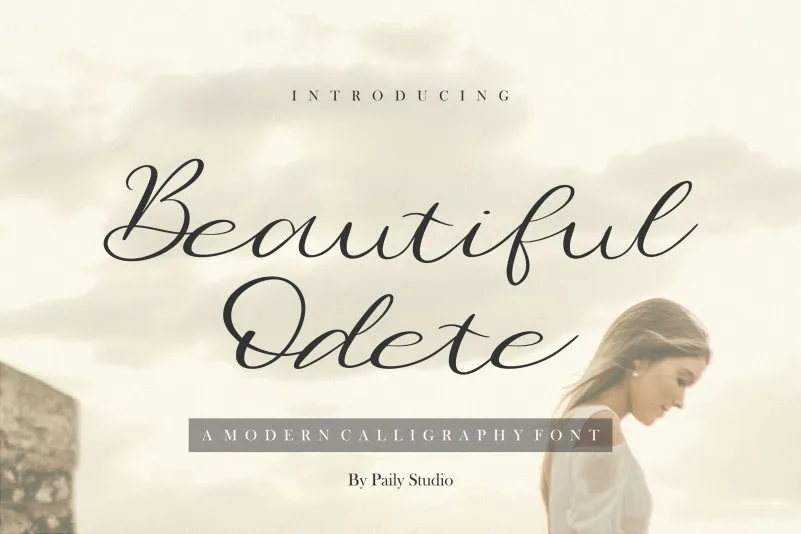
Beautiful Odete Font – Fonte Grátis
Beautiful Odete Font
A Beautiful Odete Font é uma delicada e sofisticada opção para designers que buscam adicionar um toque único a seus projetos de arte digital. Inspirada no belo estilo do caligrafia oriental, esta fonte garante uma presença elegante em qualquer aplicação, seja ela para um convite de casamento com um ar romântico ou para uma marca inovadora que precisa de personalidade forte. Ideal para designers gráficos buscando uma ferramenta versátil e sofisticada, a Beautiful Odete oferece um conjunto de características únicas que permitem criar designs distintos. Seja você criando um logotipo sedutor, preparando um cartão de nome com um toque elegante ou desenvolvendo uma postagem social capturadora, esta fonte se torna sua parceira perfeita. Com a Beautiful Odete Font, você pode esperar texturas fluidas e linhas definidas que vão desde o mais delicado até o mais bold. A sua personalização é um dos recursos essenciais desta fonte de caligrafia, permitindo ajustes sutis nas formas e na consistência do traço para criar uma experiência única em cada projeto. Para designers gráficos à procura de uma opção sofisticada que ajuda a reforçar o estilo individual de suas marcas ou eventos especiais, a Beautiful Odete Font é um recurso indispensável. Seja você criando materiais de marketing, produzindo cartões de visita ou estilizando postagens no Instagram, esta fonte oferece uma solução versátil e autêntica para expressar seu design.